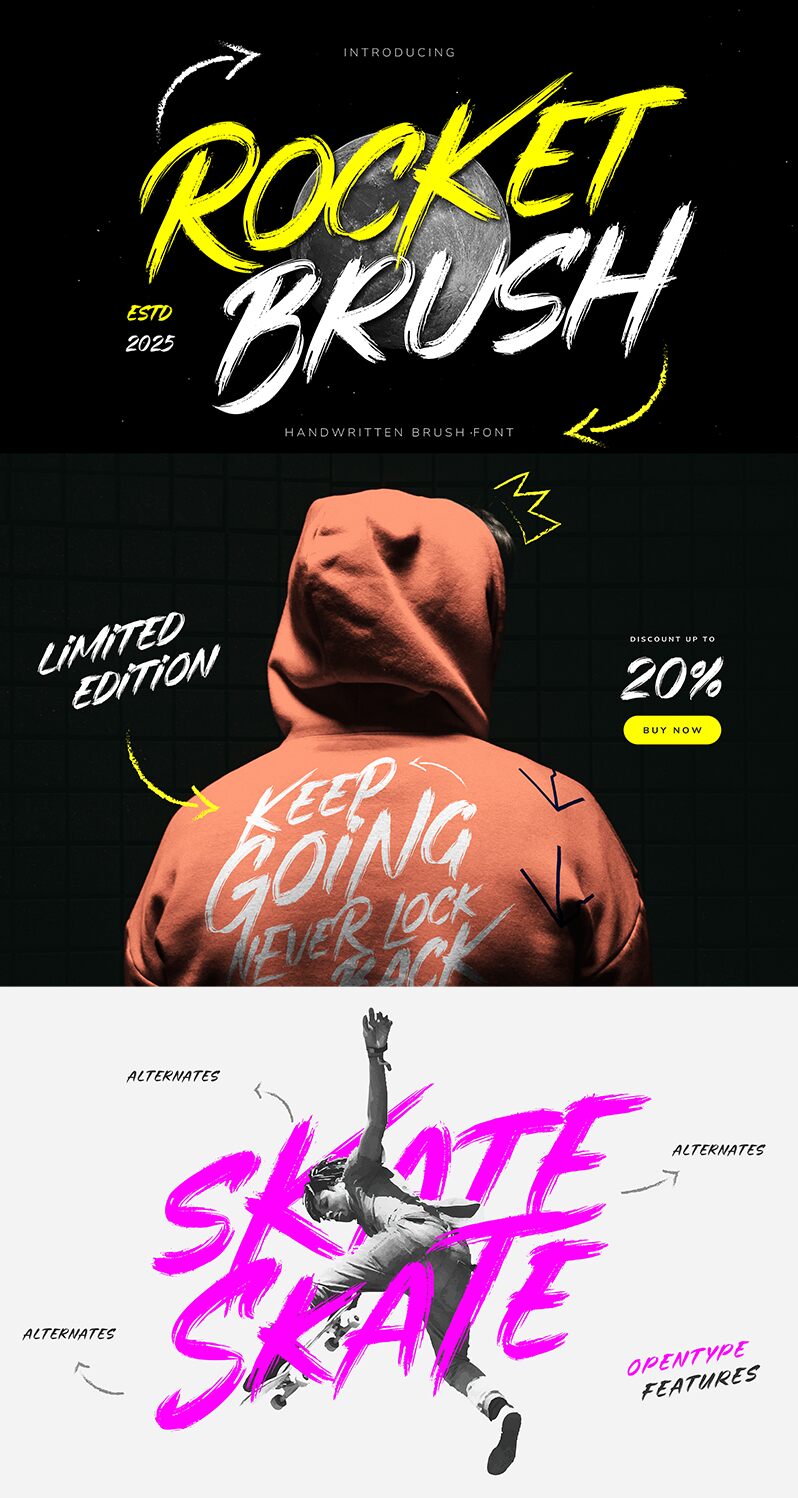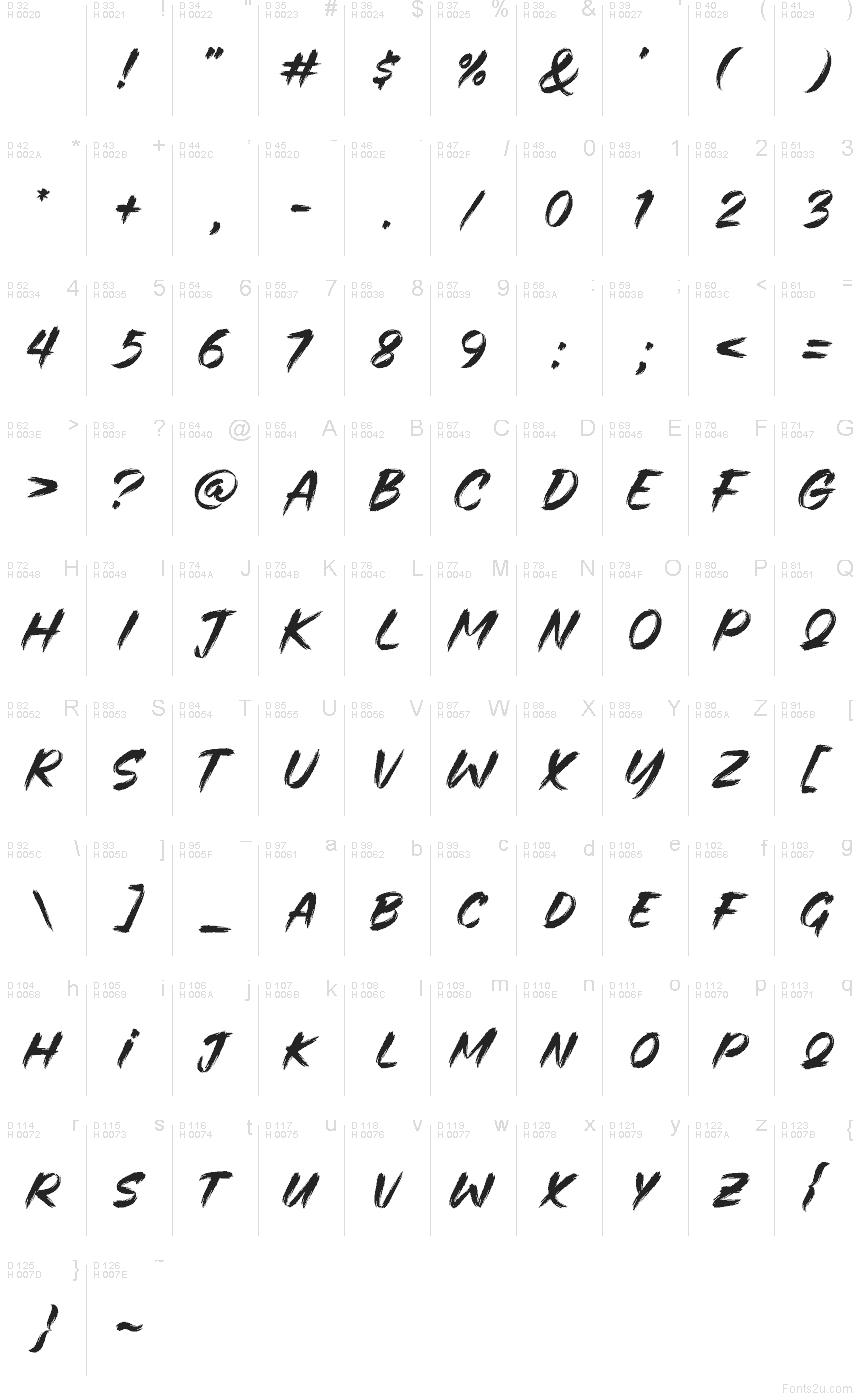
يعد Rocket Brush من Namara Creative خط فرشاة مجاني يتميز بنسيج الفرشاة الجافة السريع وضربات حادة تحافظ على مظهر الحروف الخشن من البداية للنهاية. تمنح تأثيرات الكشط المتكررة، والنهايات المدببة، وكثافة الحبر غير المنتظمة للخط طابع اللافتات المرسومة باليد، بعيداً عن أسلوب الخطوط الملساء التقليدية.
يضفي هذا النسيج الخام حيوية ممتازة على ملصقات الموسيقى، والرسوم الرياضية، وتصاميم أزياء الشارع، وصور مصغرة للفيديو، ومنشورات الفعاليات، حيث تحتاج الكلمات القصيرة إلى الحركة والتأثير الخشن. كما يمكنه إضفاء طابع مميز على التغليف أو ترويسات التواصل الاجتماعي، خاصة عندما يحتاج المشروع إلى طاقة تعبيرية تشبه الرسم بالفرشاة بدلاً من خطوط أقلام التحديد الأنيقة.
Rocket Brush